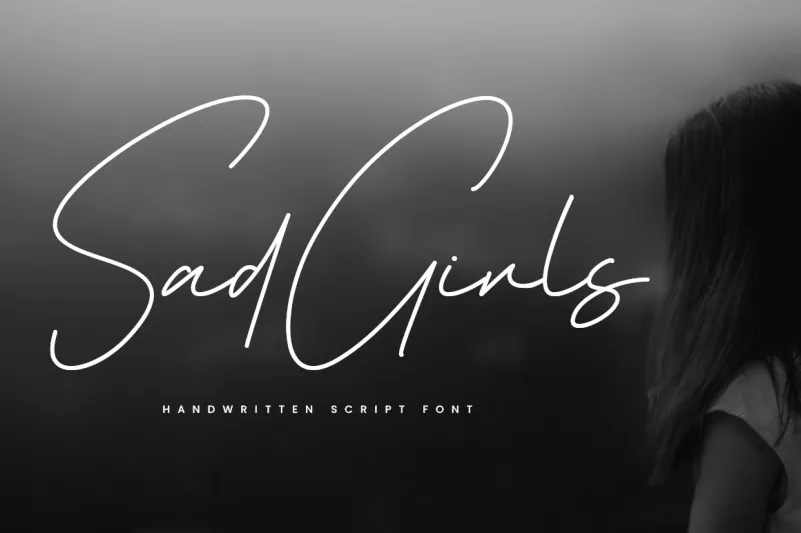
Sad Girls Font
Esta fonte é uma composição cuidadosa de traços elegantes, criada com a sensação suave de um penhoar rápido. Desenvolvida pelo font designer RasdiType, ela preserva as influências clássicas e refinadas da caligrafia enquanto mantém um toque contemporâneo e atual. Quem já testou essa fonte não pode resistir a ela; ela é uma dádiva para qualquer projeto, ajudando a elevá-lo ao próximo nível. Seja você designer de gráficos ou profissional que está buscando dar uma nova identidade visual a um projeto, esta fonte será definitivamente a escolha certa. Adquira-a agora e enriqueça sua paleta de ferramentas de design!